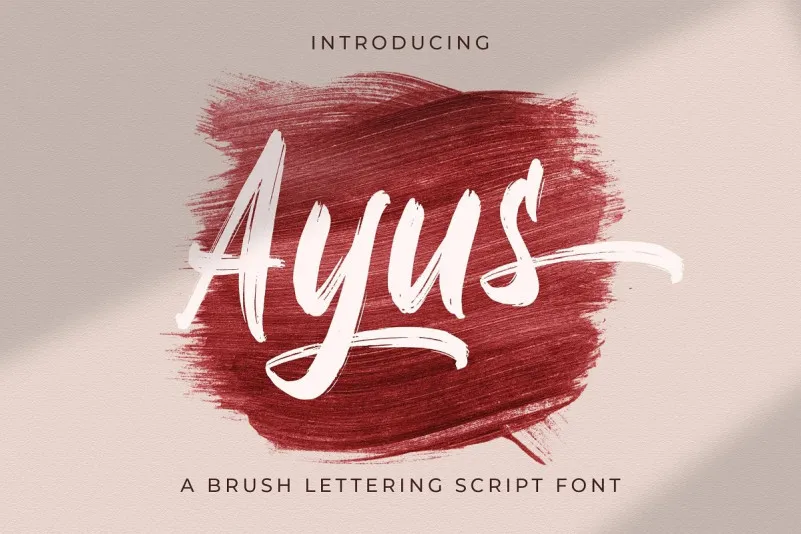
A Ayus Brush Font é uma fonte script que surge do imaginário criativo de StringLabs, uma equipe dedicada à criação de estilos únicos e memoráveis para designers. Desenvolvida com a ajuda de um pincel, essa fonte apresenta linhas com alta contraste, garantindo um visual limpo e profissional que encaixa-se perfeitamente em designs de escrita ou logotipos. Suas curvas fluidas e bordas levemente arredondadas proporcionam uma aparência elegante e sofisticada, ideal para aplicar em designs variados, desde cartazes promocionais até elementos gráficos de sites. Se você é um designer que busca novas maneiras de expressar a sua criatividade, a Ayus Brush Font pode ser uma escolha perfeita para iluminar seus projetos com seu estilo único e lindo.